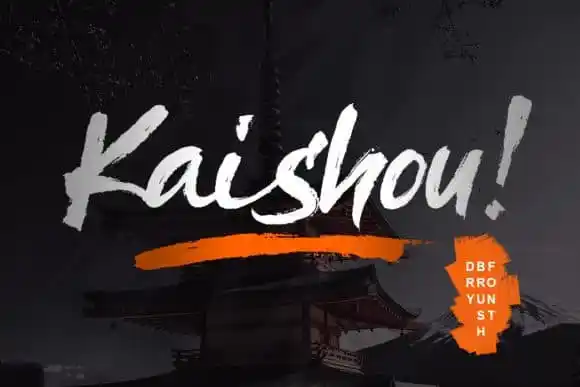
Kaishou Brush Font – Download Grátis
A Kaishou Brush Font é uma fonte script moderna que pode transformar seu texto em elegante, luxuoso e contemporâneo. Desenvolvida pelo talentoso designer Dwi Ahidian de 99designs, essa fonte se destaca como um tipo feito para o uso na pintura à mão sequencial. Com sua versatilidade inigualável, você pode usá-la em projetos DIY e torná-los incrivelmente únicos e bonitos. Seja para rótulos, letras de gráficos ou qualquer outro projeto que exija personalização, a Kaishou Brush Font tem o potencial de tornar seu trabalho ainda mais especial. Sua elegância única vem em uma variedade de formatos, permitindo uma infinidade de possibilidades criativas para designers e artistas.